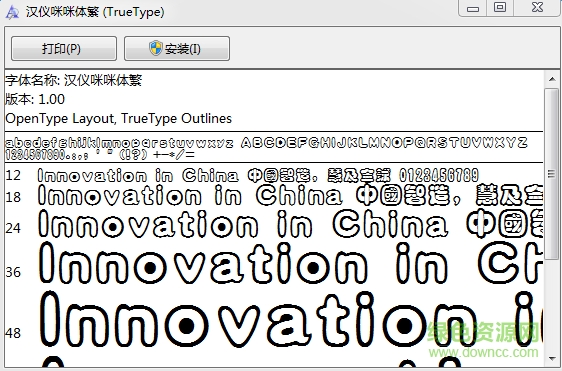
軟件介紹 軟件標(biāo)簽: 漢儀字體 字體 漢儀咪咪體繁是一款獨具特色的繁體字,這種繁字體不像其他的字體那樣是實心的,它是空心的,字體邊緣卻是下筆很重,顯得很濃厚,歡迎大家來綠色資源網(wǎng)下載。安裝說明:1.在綠色資源網(wǎng)下載字體包,并解壓縮2.最簡單的安裝方法:雙擊字體文件,點擊安裝按鈕即可2.批量安裝方法:將字體文件放到C:\Windows\Fonts溫馨提示:本站所有字體資源僅供個人學(xué)習(xí)與參考,如需商業(yè)使用請到相關(guān)官網(wǎng)授權(quán) 本字體如果商用,請聯(lián)系漢儀字體官方獲得授權(quán)。 軟件截圖 上一張下一張(1 / 1) 安裝詳細截圖 其他版本下載 標(biāo)題 大小 更新日期 下載 下載地址 電腦版 漢儀咪咪體繁 點擊報錯 軟件無法下載或下載后無法使用,請點擊報錯,謝謝! 關(guān)閉報錯反饋 請描述您所遇到的錯誤,我們將盡快予以修正,謝謝! *必填項,請輸入內(nèi)容 本類最新 漢儀孟瑞體ttf v1.0 官方版 漢儀字庫免費 132款 阿里巴巴普惠字體 官方ttf版 漢儀字體打包大全 for Mac 蘋果電腦版_ 共131款字體 漢儀純愛情書拼音體 ttf版 漢儀北魏寫經(jīng)w字體 免費版 相關(guān)文章 Photoshop字體安裝使用方法和技巧 如何解決“無法新增字體”問題 Win 7系統(tǒng)安裝字體方法 網(wǎng)頁字體大小設(shè)置方法 怎么改網(wǎng)頁字體大小 在Linux系統(tǒng)中安裝字體的幾種方法 windows7字體顯示問題:打開某些程序的時候顯示的是亂碼 用戶評論 熱門評論 最新評論 發(fā)表評論 查看所有評論(0) 昵稱: 請不要評論無意義或臟話,我們所有評論會有人工審核. 字數(shù): 0/500 (您的評論需要經(jīng)過審核才能顯示)